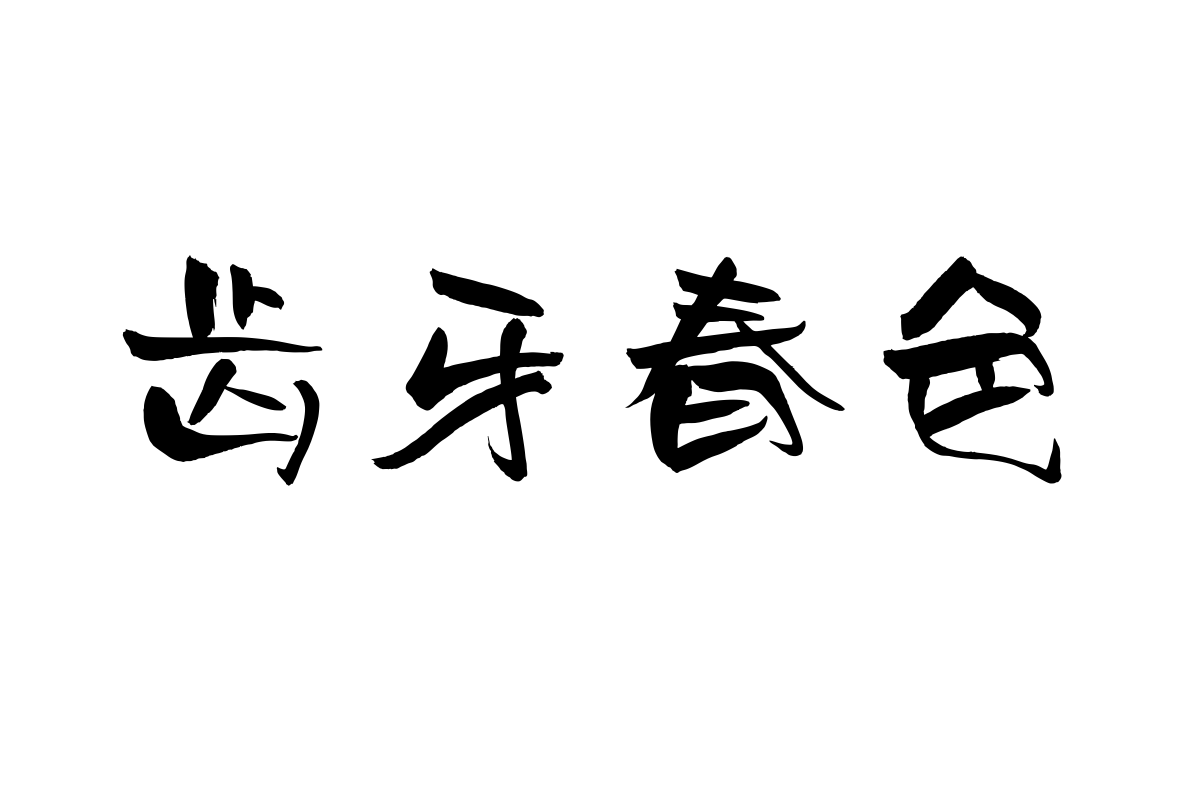
汉仪尚巍花语体是一款具有独特风格的字体,它以优雅、精致为特点,适合用于各种需要展现高雅气质的场合。这款字体采用了现代的设计手法,将传统的汉字与现代元素相结合,使得字体更加符合现代人的审美需求。
在字形结构上,汉仪尚巍花语体保持了传统汉字的基本形态,同时在笔画的处理上进行了创新,使得字体更加流畅、自然。这种设计使得字体既有古典的韵味,又不失现代感,非常适合用于标题、正文等需要突出重点的文字。
在字重和大小方面,汉仪尚巍花语体提供了多种选择,可以满足不同场景的需求。无论是用于书籍、杂志还是网页设计,都可以轻松找到合适的字重和大小,让文字更好地融入整体风格中。
此外,汉仪尚巍花语体还注重细节处理,如笔画的粗细、间距的大小等,都经过精心设计,使得字体更加美观大方。同时,这款字体还支持个性化设置,用户可以根据自己的喜好对字体进行修改和调整,使其更加符合个人的需求。
总之,汉仪尚巍花语体是一款集优雅、精致于一身的字体,无论是用于印刷品还是网络媒体,都能展现出独特的魅力。